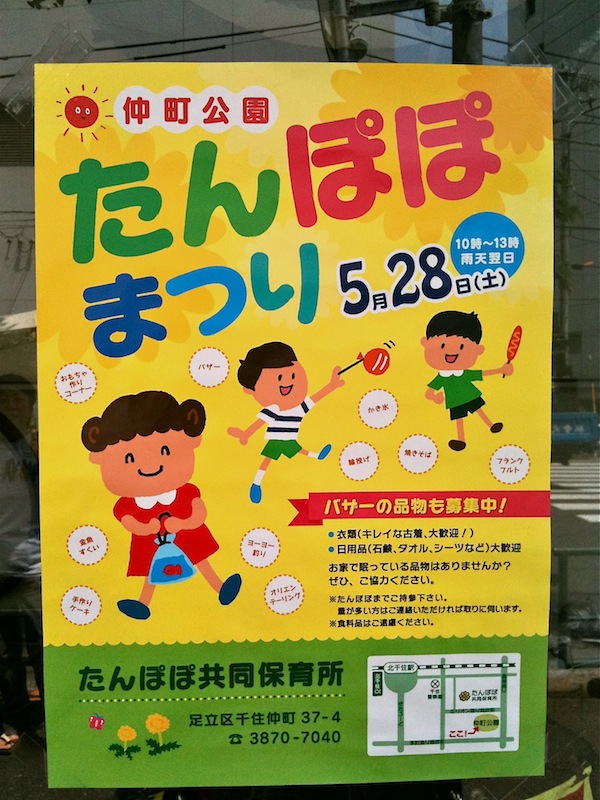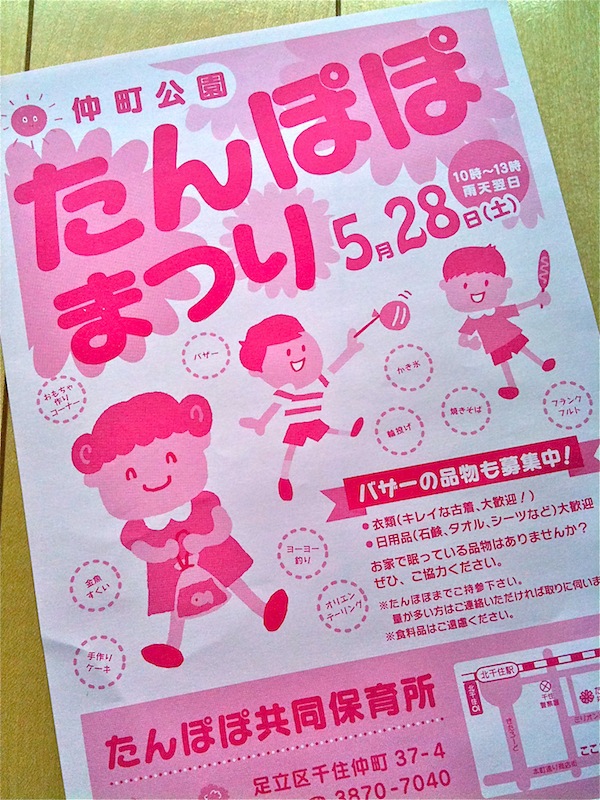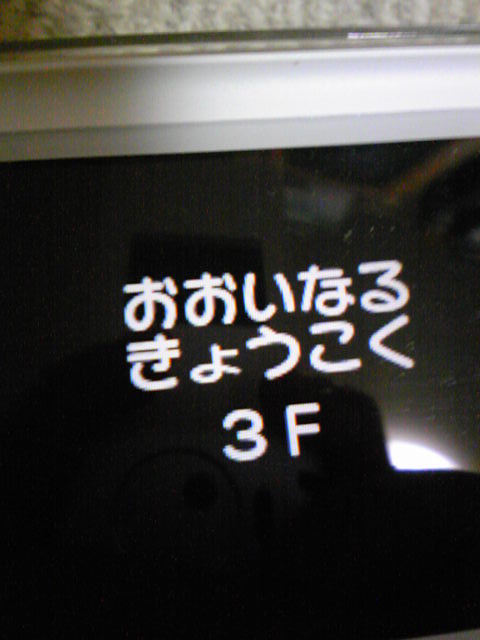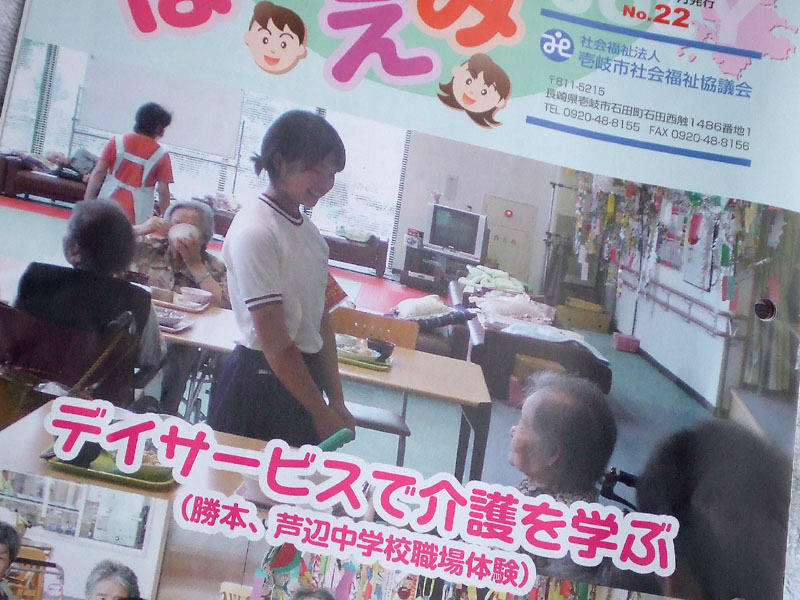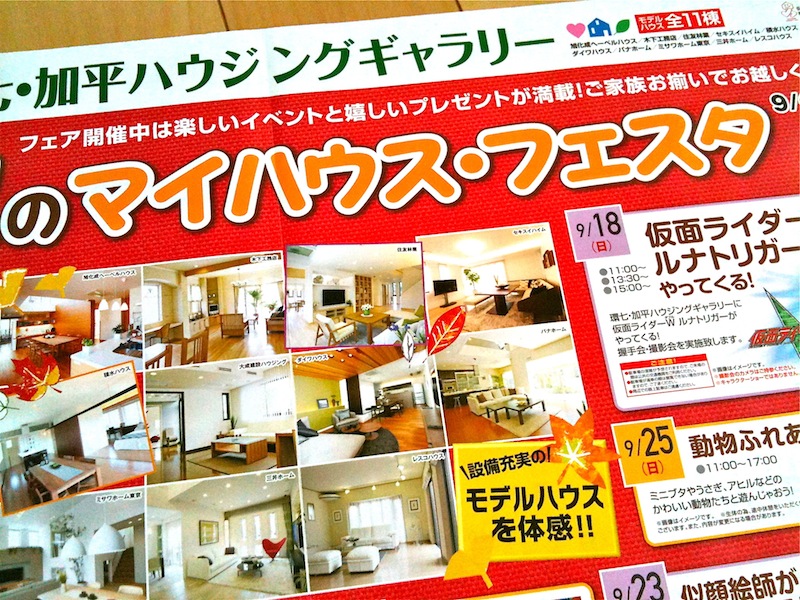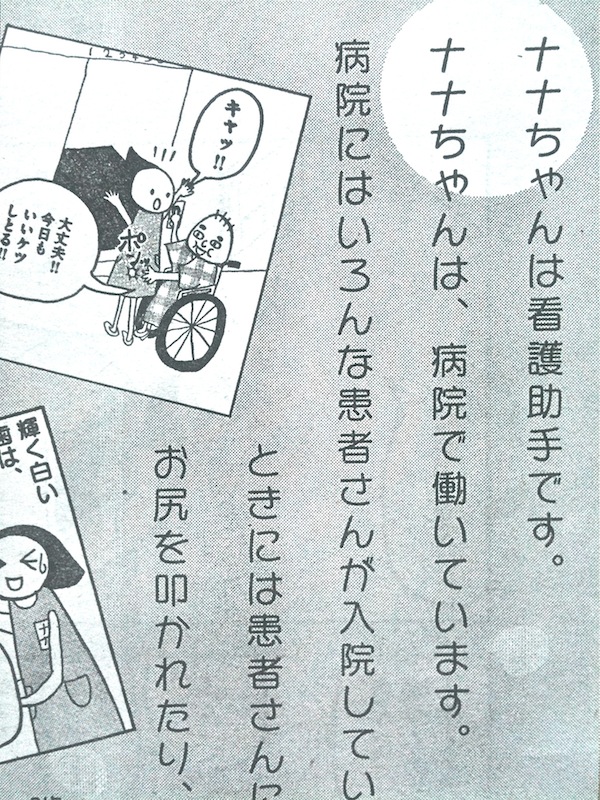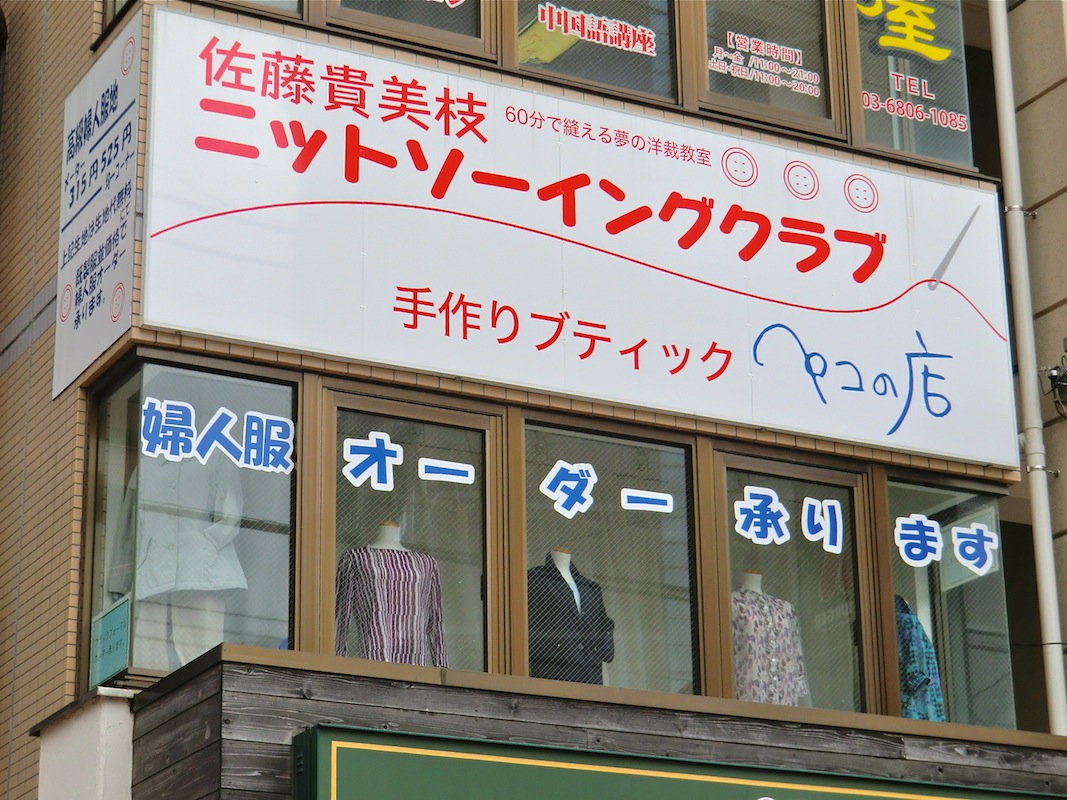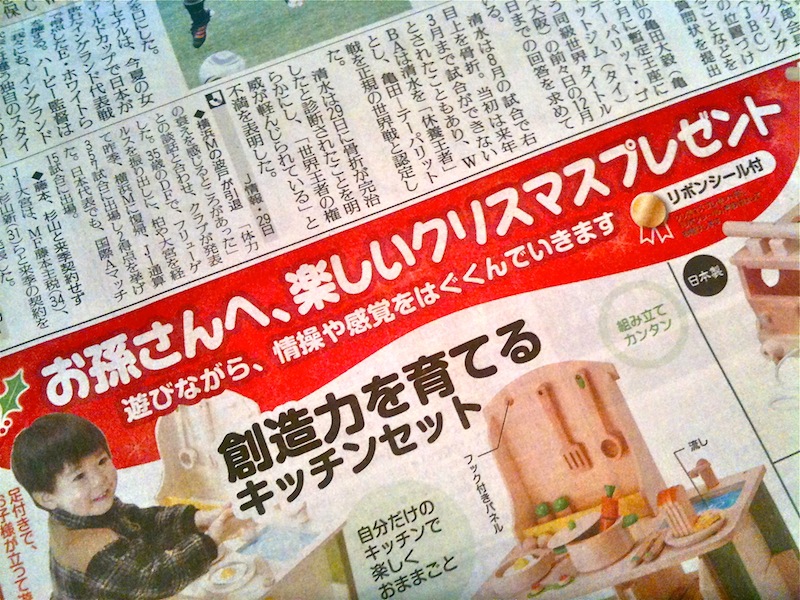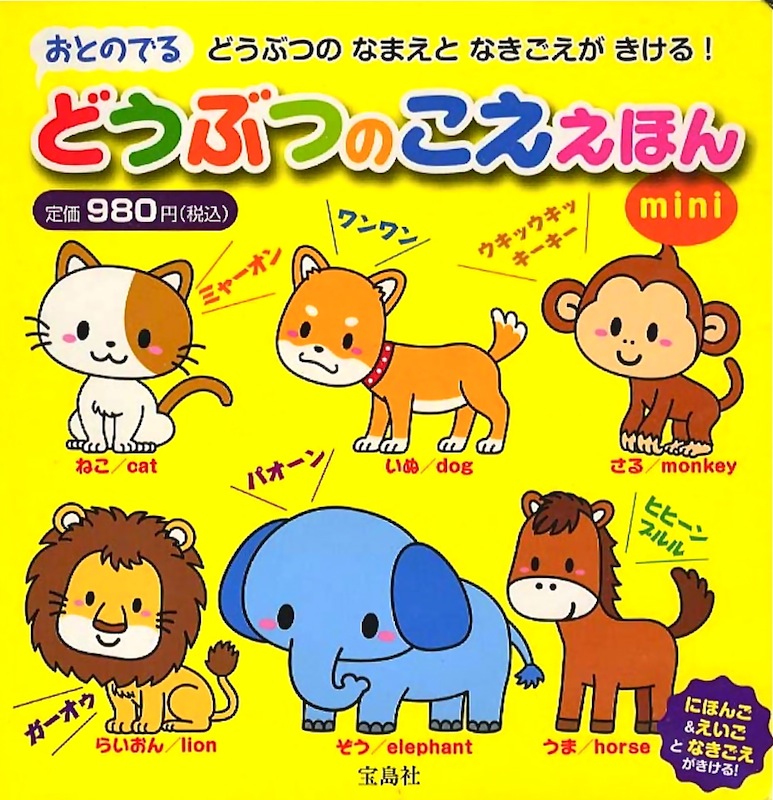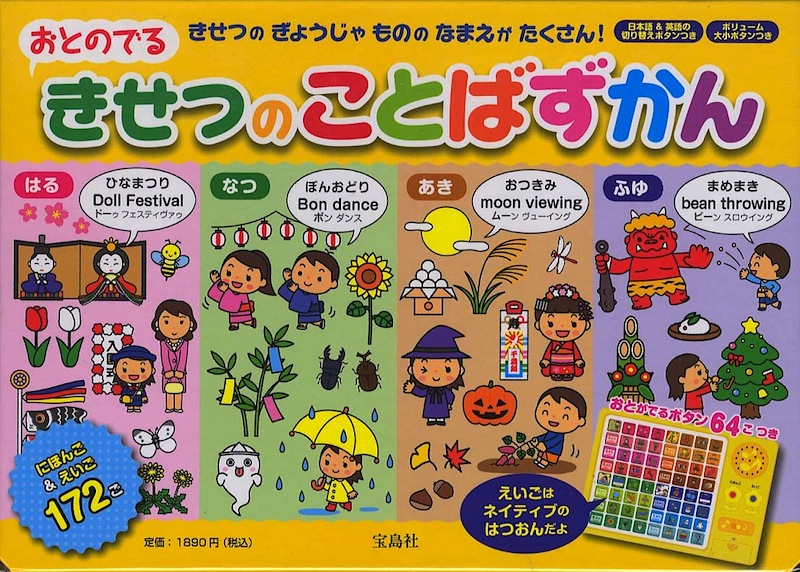
漫画の扉ページ  さとうゆたか  2012年12月20日(木) 17:00
ビッグコミックスピリッツで連載中の
「水晶(スジョン)」という漫画。
お菓子の袋でキャピー書体  takumi  2012年12月10日(月) 15:49  HP
カルビーのお菓子の袋で使われていたキャピーです(オリーブとガーリック〜)。
こういう太めのウェイトのキャピーは、某フォント会社との契約でしか使えないのが残念です。
参考画像をもう1つ!(同じ商品です)
太めのキャピー……、可愛いし私も好きなんですよ。
でもタイプラボには、それに合わせる太い丸ゴシックが無いですからね…。
いつか、丸ゴシックのファミリー書体が完成したら、その時には当然「太めのキャピー」と組み合わせたフォントも作るつもりでいます。
いつになるやら、判りませんが…。
フキダシの中  さとうゆたか  2012年10月31日(水) 16:54
ビーラブという漫画雑誌に掲載されていたコミックスの広告。
本の表紙  さとうゆたか  2012年9月22日(土) 11:26
書名:リアリティー
著者:山口まあら
発行:星雲社
キャンペーンロゴ  さとうゆたか  2012年9月13日(木) 16:42
永谷園のキャンペーンです。
本の表紙  さとうゆたか  2012年7月31日(火) 10:12
書名:ペットボトルおもちゃ
著者:すずお泰樹
発行:いかだ社
小さい文字にはハッピー書体が使われています。
本の表紙  さとうゆたか  2012年7月13日(金) 16:48
書名:ココロ・ファインダ
著者:相沢沙呼
発行:光文社
エンジョイエコカード  さとうゆたか  2012年7月1日(日) 16:57
5月末に行った大阪。
地下鉄淀屋橋駅のホームから見える広告。